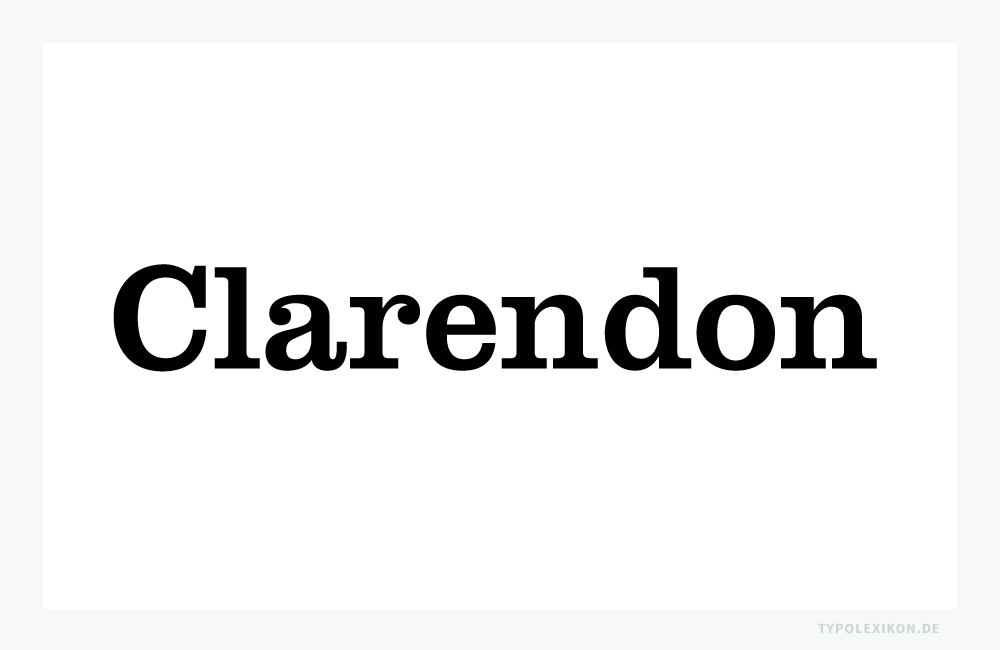
Eidenbenz, Hermann
Schweizer Grafikdesigner, Typograf, Fotograf, Lehrer und Schriftgestalter. Geboren am 4. September 1902 in Cannanore (Kannur) in British India als Sohn des Schweizer Kaufmanns Hermann Samuel Eidenbenz (1868–1939) und einer deutschen Mutter. Gestorben am 25. Februar 1993 in Basel in der Schweiz. Bekannt wurde Hermann Eidenbenz durch seine grafischen Plakate, Banknotenentwürfe und die Neuinterpretation der Druckschrift »Clarendon«, einer Egyptienne des englischen Schriftgießers Benjamin Fox (o.A.–1877). 1)
Nach seiner Schulzeit in der deutschsprachigen Schweiz entschied sich Hermann Eidenbenz für eine Ausbildung zum Lithografen und Gebrauchsgrafiker; von 1919 bis 1922 als Lehrling bei Orell Füssli in Zürich und im Anschluss von 1922 bis 1923 als Berufsschüler an der Züricher Kunstgewerbeschule.
Von 1923 bis 1926 zog es Eidenbenz nach Berlin, wo er als Werbe- und Gebrauchsgrafiker für unterschiedliche Firmen tätig war. Von 1926 bis 1932 war er Lehrer für Schrift und Grafik an der Kunst- und Handwerkerschule in Magdeburg in Sachsen (heute Landeshauptstadt von Sachsen-Anhalt).
Vor der endgültigen Machtergreifung der Nationalsozialisten zog er sich um 1932 in die neutrale Schweiz zurück, wo er mit seinen beiden Brüdern Reinhold (1907–1988) und Willy Eidenbenz (1909–1998) ein Foto- und Grafikatelier in Basel gründete. 1940 bis 1943 unterrichtete er dort auch an der Allgemeinen Gewerbeschule. 1945 Heirat mit Lotte Christoffel.
Plakat »Swissair« von Hermann Eidenbenz (1902–1993) aus dem Jahre 1948. Auftraggeber: Swissair AG, Schweizerische Luftverkehr-Aktiengesellschaft, Kloten, Schweiz (1931–2002).
Nach dem Zweiten Weltkrieg kehrte Eidenbenz dann wieder nach Deutschland zurück und übernahm 1953 für etwas mehr als ein Jahr die Leitung der Abteilung Gebrauchsgrafik an der niedersächsischen Werkkunstschule in Braunschweig. 2)
1953 fertigte Hermann Eidenbenz im Auftrag der Haas´schen Schriftgießerei in Frankfurt am Main die Reinzeichnungen der »Clarendon«, welche dort als Akzidenzschrift für den Handsatz in einem normalen, leichten und fetten Schriftschnitt produziert wurden.
Der Nachschnitt der »Clarendon« ist eine Überarbeitung einer Egyptienne (Slab Serif) mit runden Serifenübergängen des englischen Schriftgießers Benjamin Fox (o.A.–1877), die Hermann Eidenbenz 1953 im Auftrag der Haas´schen Schriftgießerei in Frankfurt neu zeichnete. Schriftprobe: Clarendon LT Std Roman von Adobe.
1962 wurde bei der Stempel AG (in der Folge der Haas´schen Schriftgießerei) für den Hand- und Maschinensatz als Werksatzschrift noch eine magere und halbfette Variante und 1964 eine breitfette Variante vorgestellt, welche 1965 durch einen schmalmageren Schnitt ergänzt wurde.
Mit Beginn des optomechanischen Schriftsatzes (Fotosatz) wurde die Clarendon bei Linotype (in der Folge der Stempel AG) und anderen Schriftbibliotheken (z.B. H. Berhold AG und URW) zu einer umfangreichen Schriftfamilie ausgebaut.
Von 1955 bis 1967 war Hermann Eidenbenz als Art Director (Grafikdesigner) für die Zigarettenmarke Reemtsma in Hamburg tätig. Zu seinem Repertoire als freiberuflicher Grafiker zählten insbesondere Signete (z.B. das Stadtwappen Basel), illustrative Plakate (z.B. für Swissair), 3)  Banknoten (z.B. erste Serie der D-Mark-Banknoten und Schweizer Franken, Serie 5 ab 1956) sowie Briefmarken (z.B. die 1955 von der Deutschen Bundespost herausgegebene 10 Pfennig Briefmarke zum 100. Todestag des Mathematikers und Astronomen C. F. Gauss, 1777–1855).
Hermann Eidenbenz war auch als leidenschaftlicher Fotograf bekannt. So nahm er beispielsweise regelmäßig an fotografischen Gruppenausstellungen und Sammelpublikationen teil und war – wie sein Bruder Willi – Mitglied des Schweizerischer Photographen Verband (SPhV). Eidenbenz starb am 25. Februar 1993 im Alter von 90 Jahren in Basel in der Schweiz.
↑1 Anmerkung: Semantisch rührt die Bezeichnung »Clarendon« von »Earl of Clarendon«, einem erblichen britischen Adelstitel.
↑2 Literaturempfehlung: Klein, Sarah (Hrsg.), François Rappo und Roland Früh: Hermann Eidenbenz’ Grafikunterricht, Dokumente 1926–1955, Triest Verlag, Zürich, 2019, ISBN-10 3038630357, ISBN-13 978-3038630357.